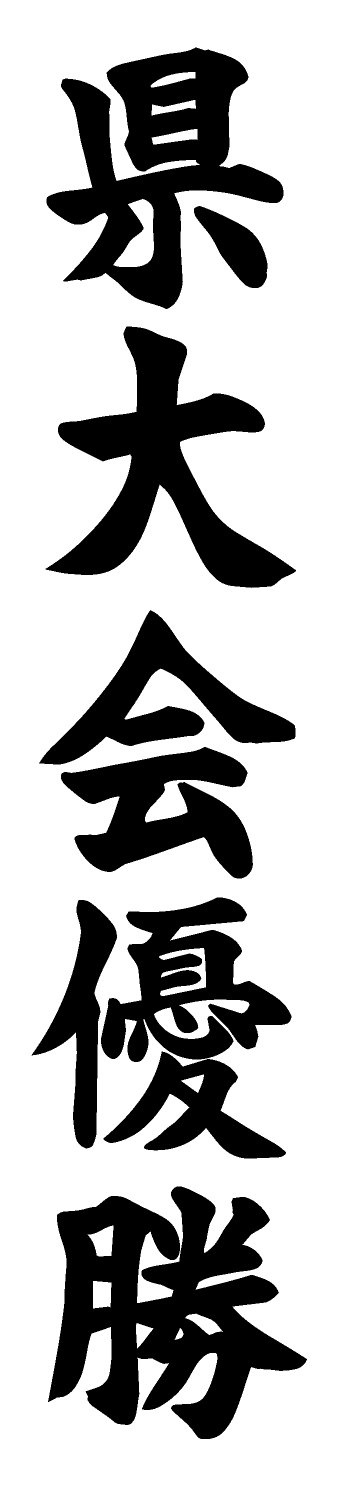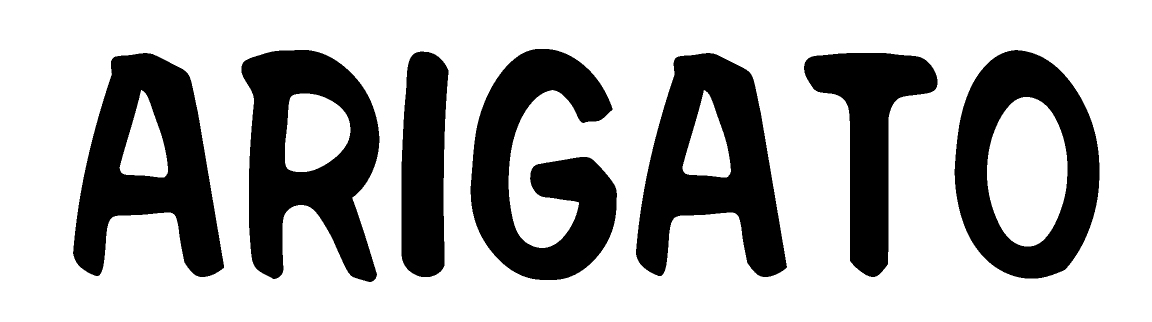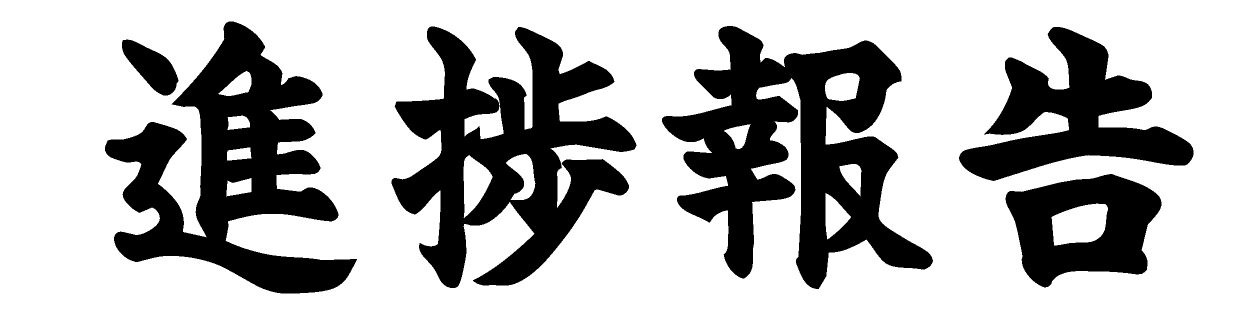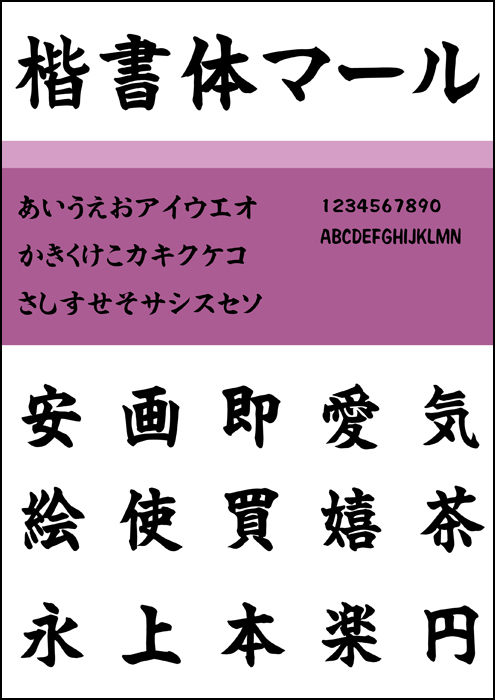
【書:織田八良】
【概要】
弊社書籍『ディスプレイ書体集 楷書体字典』(織田八良 著)をフォント化したものです。楷書体は、漢字の書体の基本とされ、正確に伝達することを意図して生み出されました。チラシやポスター、賞状、表札、各種資料タイトルなど、幅広く愛用されています。フォントフォーマットはTrueTypeです。印刷物への使用など一般的な商業利用は追加料金なしで可能です。詳細については、上記リンク「使用許諾範囲」を、ご購入前に必ずご確認ください。